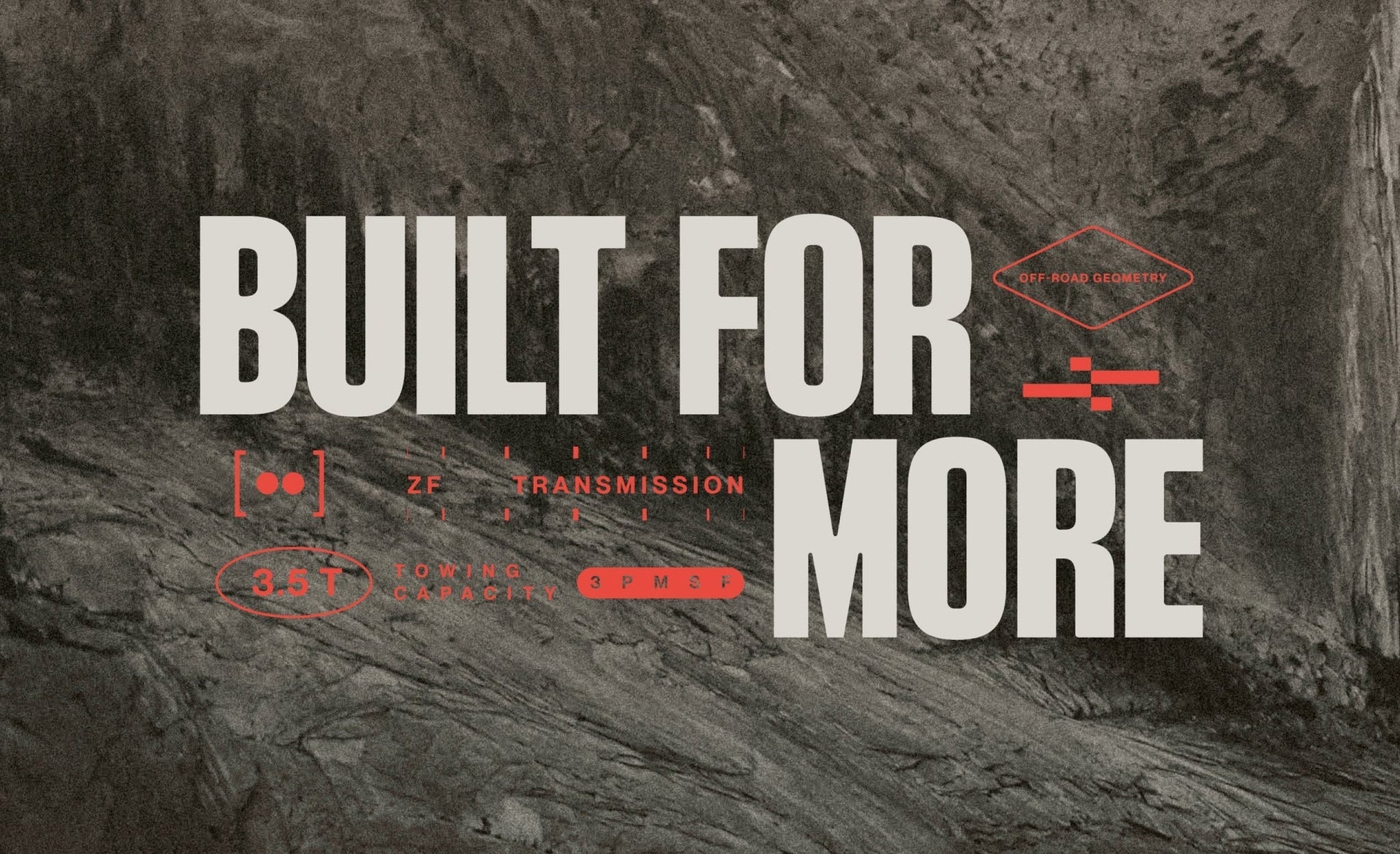
Wonderhood Design a créé une nouvelle identité complète pour INEOS Automotive,
parallèlement à une campagne de marque mondiale pour l'INEOS Grenadier lancée la même année. La nouvelle identité est une re complète de la marque sur tous les points de contact et est désormais active sur un certain nombre de nouveaux marchés, notamment l'Europe, les États-Unis et la Chine.
La nouvelle identité a été finalisée parallèlement à un nouveau positionnement de marque, passant d'une approche purement automobile à une approche lifestyle axée sur l'aventure. Ce positionnement s'inscrit dans la nouvelle plateforme de marque d'INEOS Automotive, « Built For More », qui met l'accent sur le sentiment de liberté et les opportunités que le conducteur éprouve au volant.
Le design reflète la précision de la construction automobile, avec une sensation plus viscérale et émotionnelle au volant d'une INEOS Grenadier. Une police de caractères personnalisée, « Formula 4X4 », a été créée pour refléter la robustesse de la construction, mise en valeur par les détails usinés, gaufrés et Roundeds du véhicule, notamment le logo en relief sur le capot. « Formula 4X4 » propose également des variantes stylistiques et des glyphes sur mesure, en lien avec la précision des détails et les caractéristiques du véhicule.
Le logo INEOS Automotive prend vie grâce au mouvement inspiré du terrain tout-terrain et à une expérience de conduite plus immersive. Les principes de mouvement de la marque visent à créer cette sensation à tous les points de contact, associée à une précision d'ingénierie méticuleuse.
Un ensemble personnalisé d'icônes et de badges a également été créé pour exprimer visuellement les caractéristiques et les capacités du produit du véhicule, utilisées dans toute la marque mondiale, depuis les informations techniques sur les brochures et le site Web jusqu'aux communications et à la publicité.